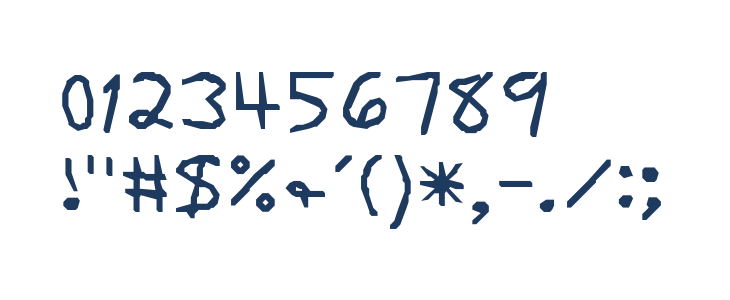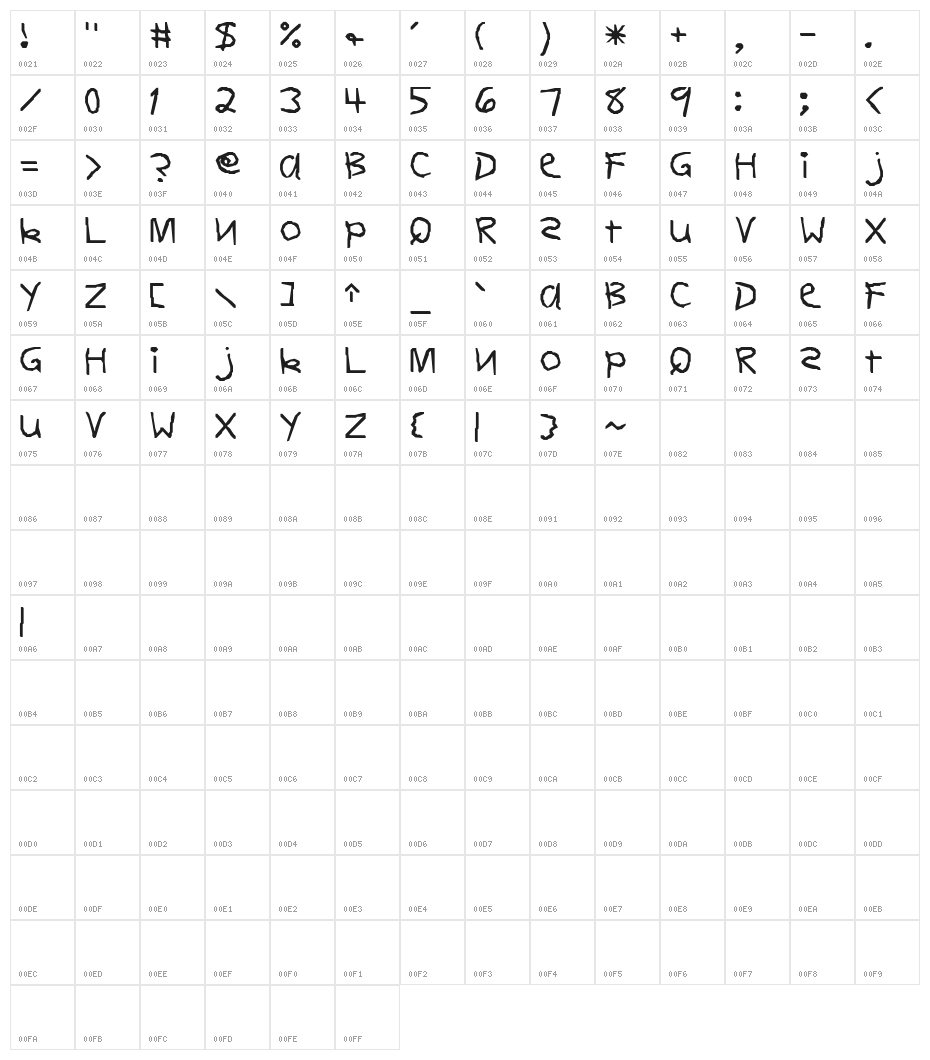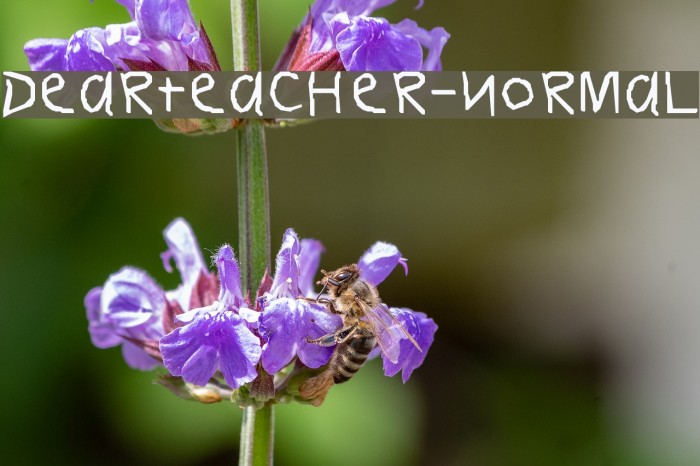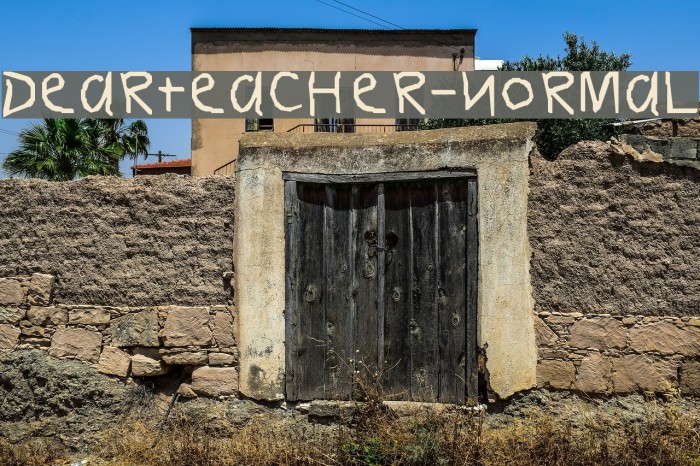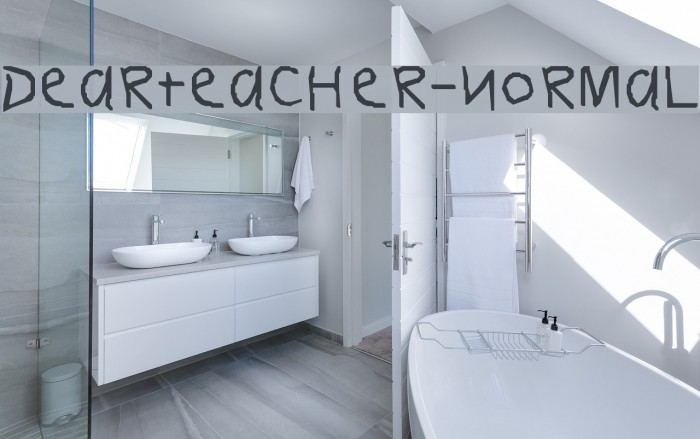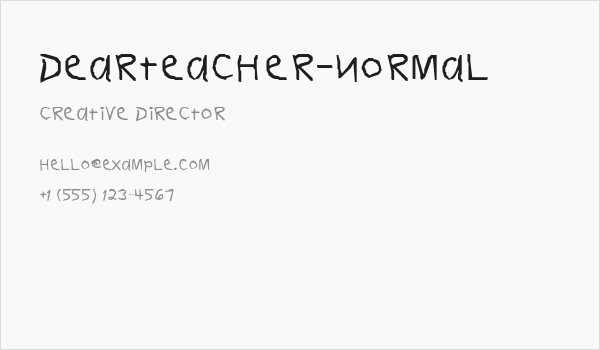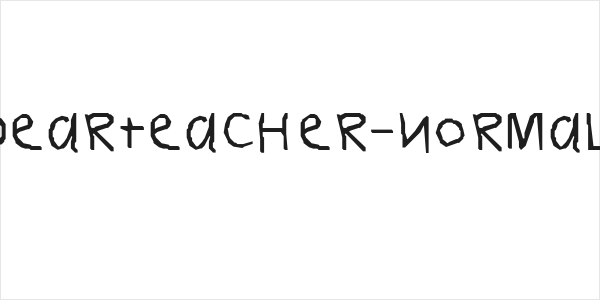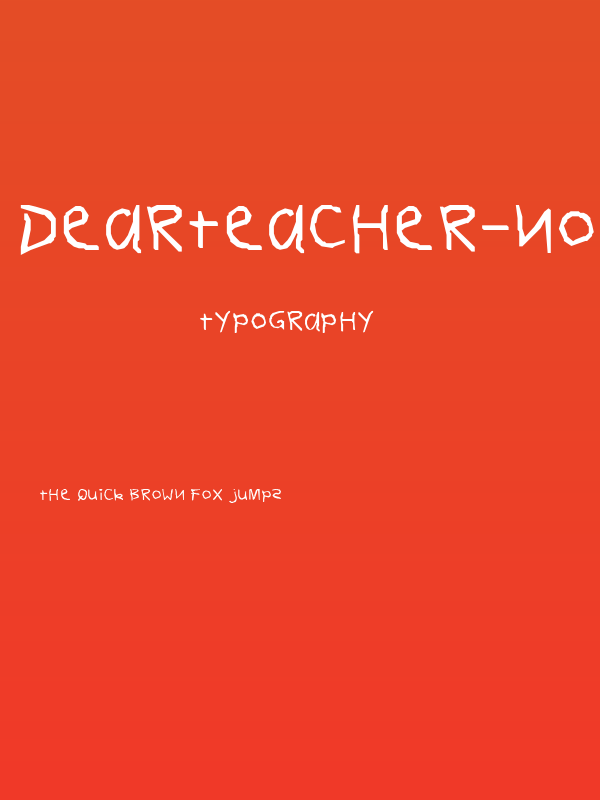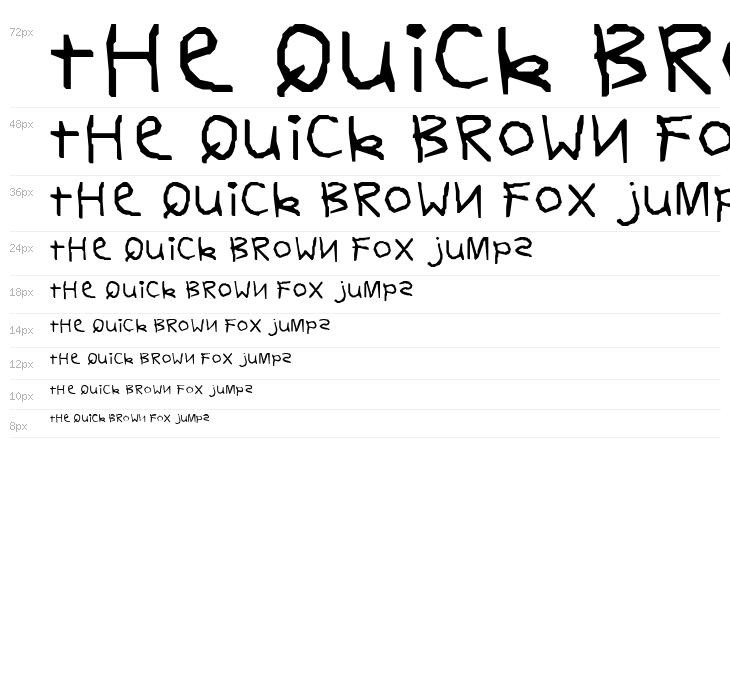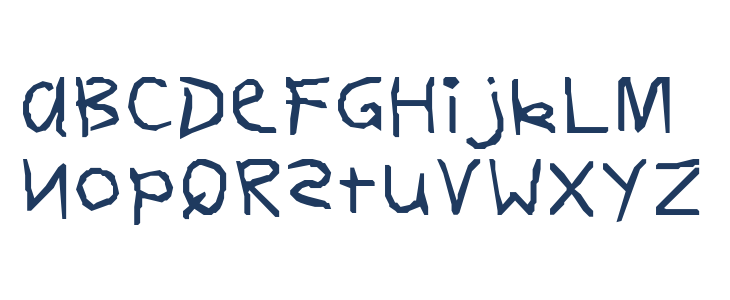
DearTeacher-Normal Font
| Общий стиль | Casual |
| Область применения | Headlines, Informal text, Creative projects |
| Рекомендуемые проекты | Ideal for greeting cards, children's books, casual invitations, and personal blogs. |